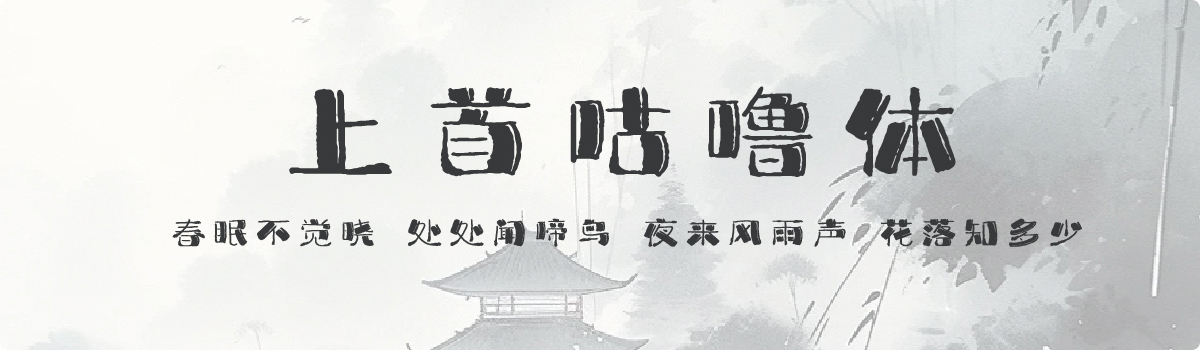
上首咕噜体
上首咕噜体,这款字体结构工整、笔画清晰,兼顾美观与易读性,适用于标题、正文、海报、包装、LOGO 等多种场景。字形优雅稳定,风格百搭耐看,适配日常排版与创意设计,让文字呈现更舒适、更具质感。上首咕噜体一笔一画,皆是细节,以均衡的比例、流畅的线条打造舒适视觉体验,字形端正大气,风格简约现代。无论是商业设计、品牌宣传还是日常排版,都能轻松驾驭,让文字更有格调与力量。上首咕噜体字体下载。